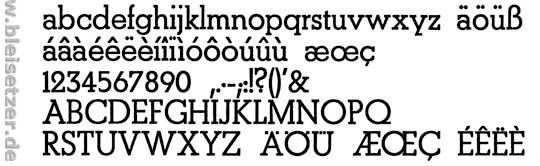
Das ist die Beton halbfett.
Man sieht es am Versal-A. Das hat oben im Dach nur einen Querbalken nach links:
Bauersche Gießerei, Frankfurt am Main
Erstguß 1931
Heinrich Jost
Das ist die Beton halbfett.